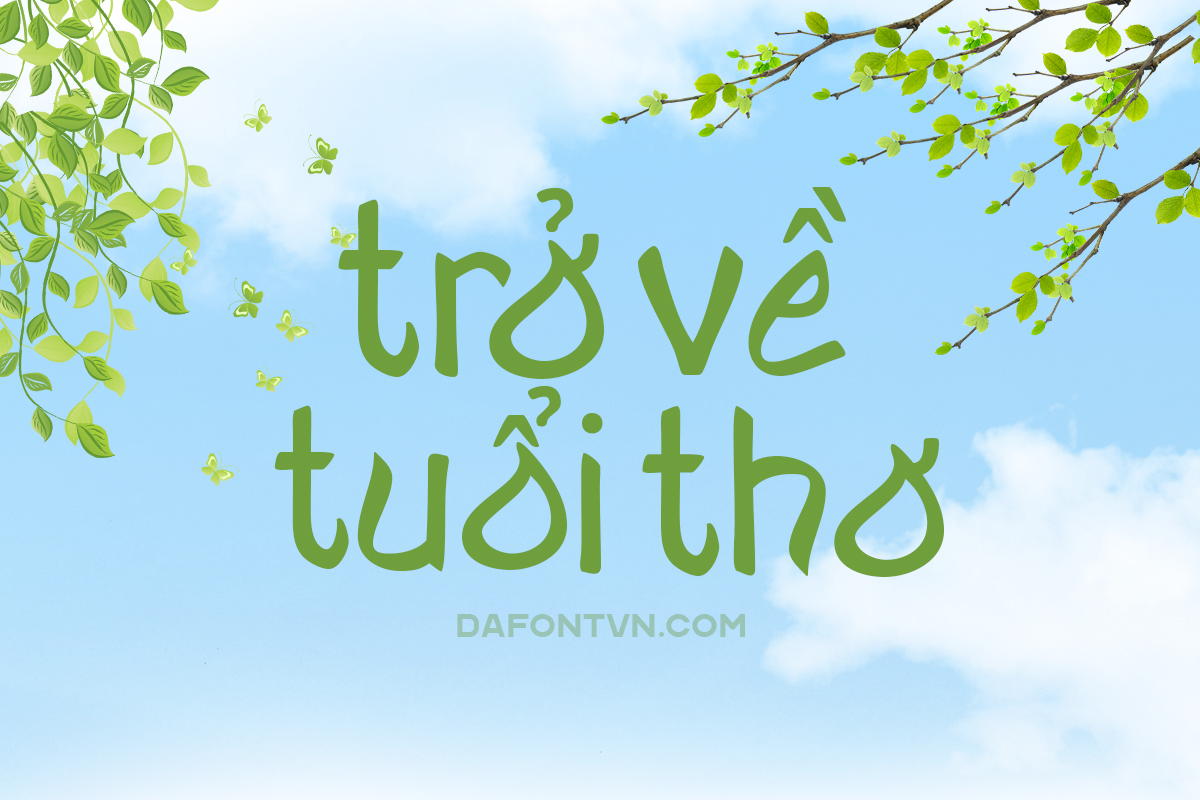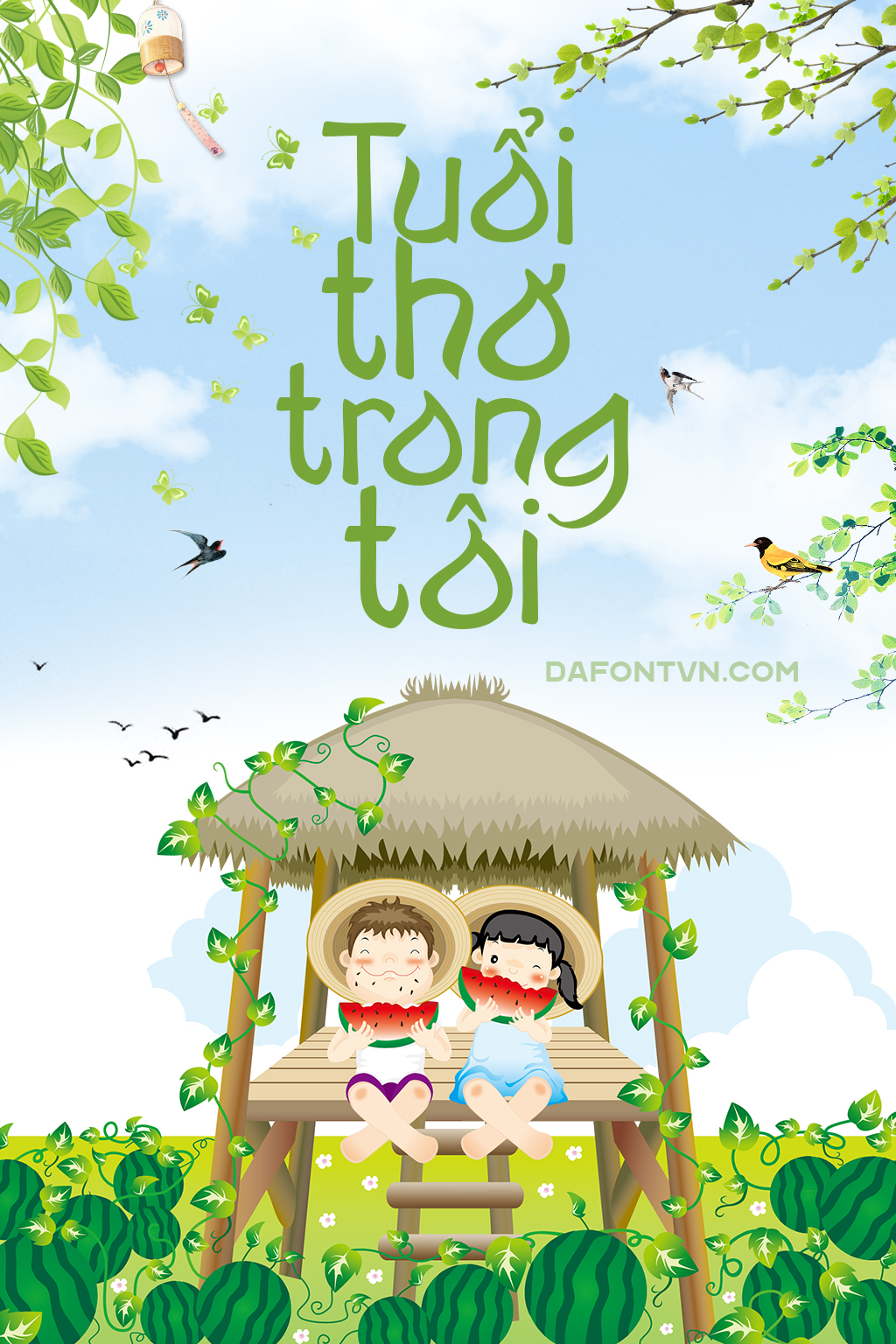
Font Qojarun việt hóa – Kiểu font thư pháp
Font Qojarun là một phông chữ được thiết kế mang phong cách từ các chữ cá Ả Rập, bạn có thể sử dụng để tạo cho các thiết kế của mình cảm giác Trung Đông chân thực.
Phông chữ này có các ký tự theo phong cách Ả Rập và phù hợp cho nhiều thiết kế khác nhau như poster, bìa sách, áp phích… Với kiểu thư pháp trang nhã của các chữ cái Ả Rập rất dễ đọc.
Font được việt hóa đầy, kerning, 1 số dấu được chỉnh sửa lại đôi chút, tối ưu hóa và mã hóa PUA để sử dụng trên bát kỳ phần mềm thiết kế hoặc phi thiết kế.
Font việt hóa Qojarun - font thư pháp đẹp